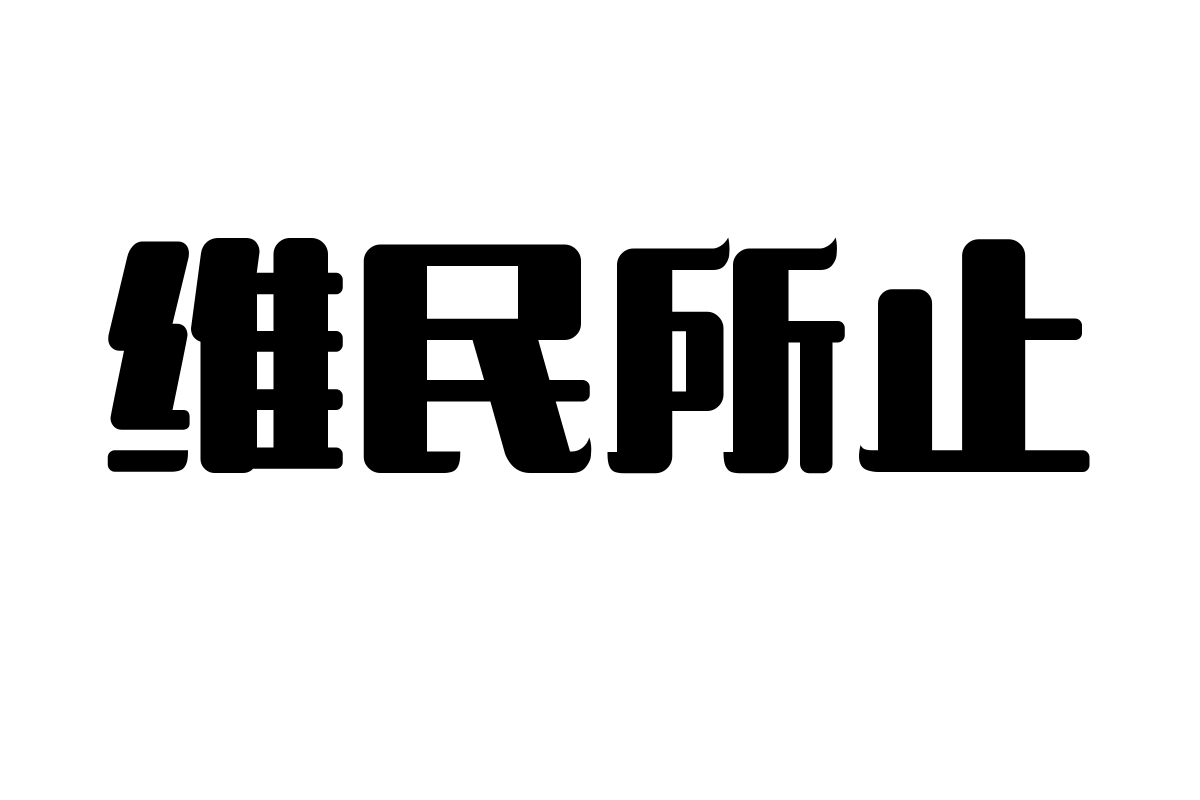
造字工房韵黑体是一款具有独特设计风格的字体,它采用了现代简约的设计元素,结合了传统的书法韵味。这款字体的特点是笔画流畅、结构紧凑,给人一种简洁而大气的感觉。同时,造字工房韵黑体还注重细节处理,每个字的间距和行距都经过精心设计,使得整个字体看起来更加整齐有序。
造字工房韵黑体适用于各种场景,如标题、正文、广告等。它的应用场景非常广泛,无论是在印刷品还是电子屏幕上,都能展现出其独特的魅力。此外,造字工房韵黑体还具有一定的可读性,即使在较小的字体尺寸下也能保证清晰的视觉效果。
总的来说,造字工房韵黑体是一款非常适合现代设计需求的字体,它既具有传统书法的韵味,又不失现代简约的风格,值得设计师们尝试使用。